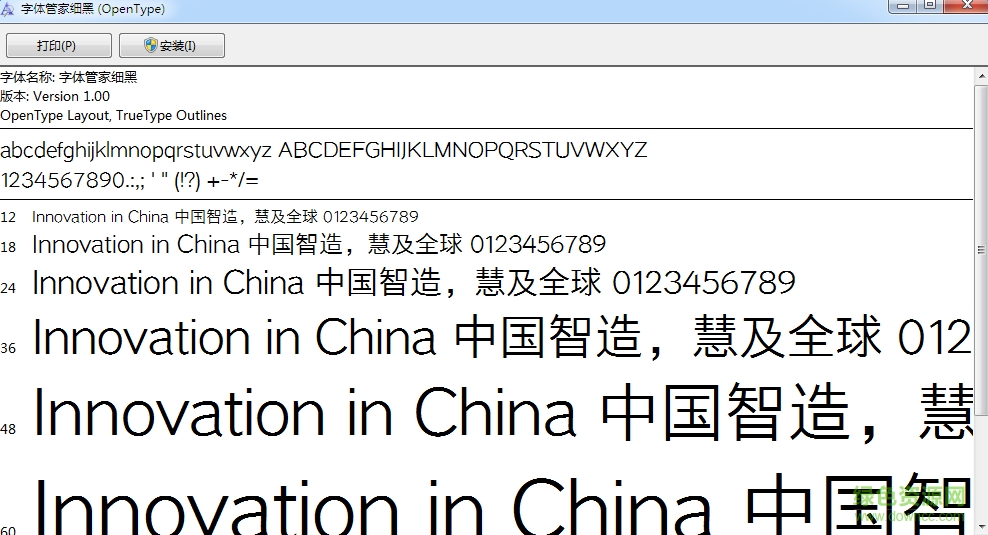
字體管家細黑體是在黑體基礎(chǔ)上減細設(shè)計而成,字形飽滿富于張力,筆畫硬朗簡潔表現(xiàn)清晰,特別是多字排在一起時,就可以展現(xiàn)出字形的連貫性和整體感,喜歡的朋友歡迎來綠色資源網(wǎng)下載使用!
字體管家細黑體字形結(jié)構(gòu)扁方、端莊,橫豎筆畫粗細比例適度、豎筆粗壯有力,布白均勻、行文貫通。粗細適中,比一般的黑體更清晰易讀,筆畫簡潔有力細微處變換靈動,即實用又富有裝飾效果。